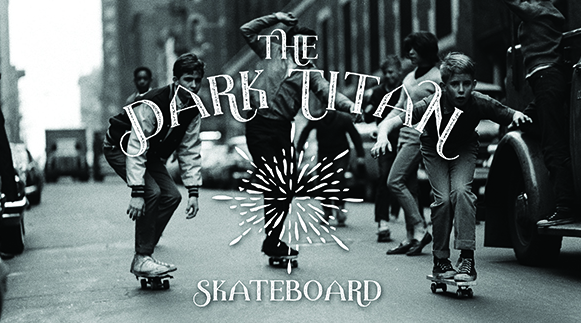
The Dark Titan Font
Olá a todos! Estou aqui para compartilhar uma descrição envolvente sobre a nossa fonte ‘The Dark Titan Font’. Esta é uma fonte demo criada pelo designer madeDeduk, um artista de design gráfico dedicado e talentoso. Nossa fonte ‘The Dark Titan Font’ é exatamente o tipo de elemento que você precisa para dar vida às suas criações digitais. Com um estilo único e impactante, esta font oferece uma aparição poderosa e elegante, combinando força com sofisticação. Seja em design gráfico, branding ou editoração de texto, essa fonte vai brilhar onde quer que ela seja aplicada. Se você está interessado em obter a versão completa da nossa fonte, apenas clique no link abaixo. Você encontrará mais detalhes sobre como baixar o arquivo completo da fonte e a descrição da fonte original feita pelo designer. Lembre-se de visitar nosso catálogo para explorar mais recursos gráficos criativos.